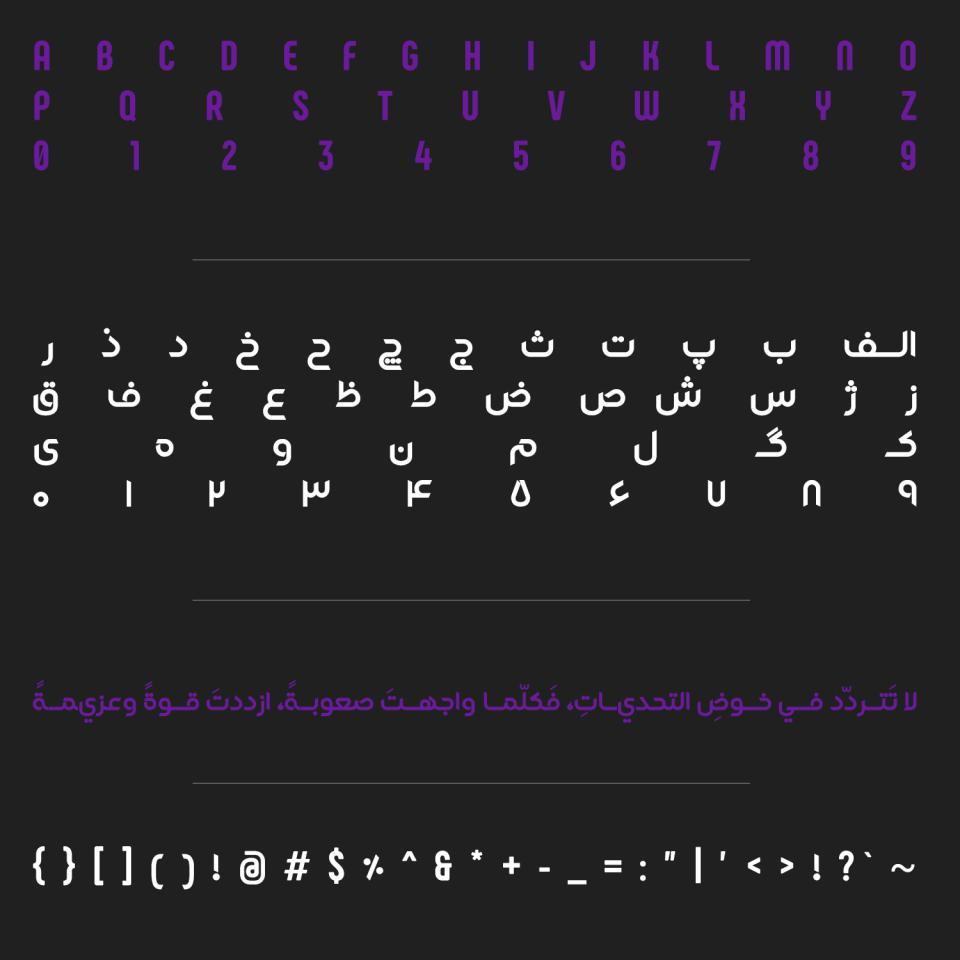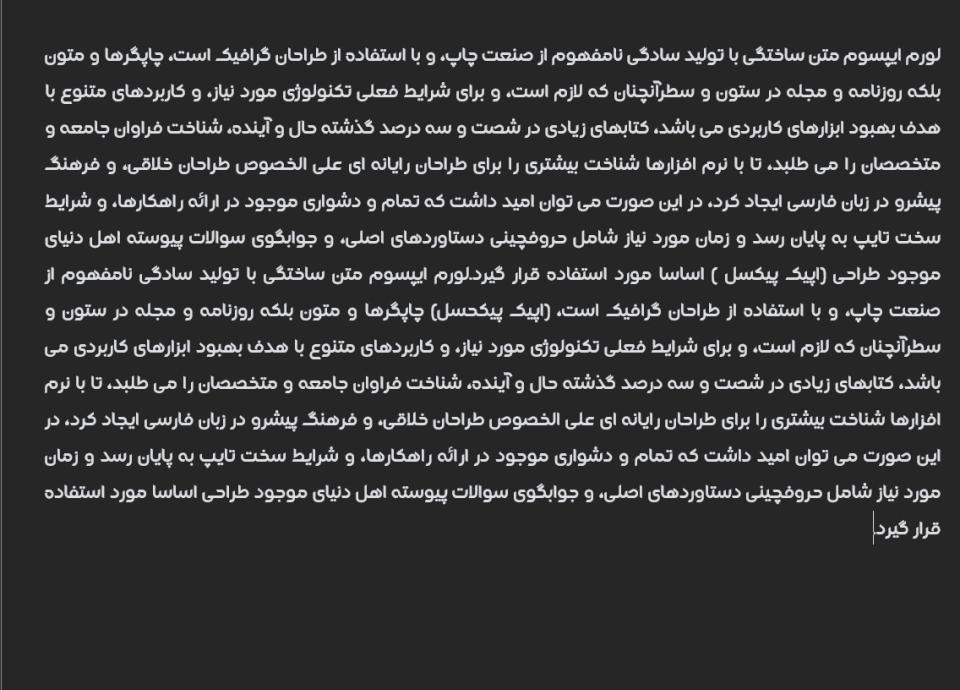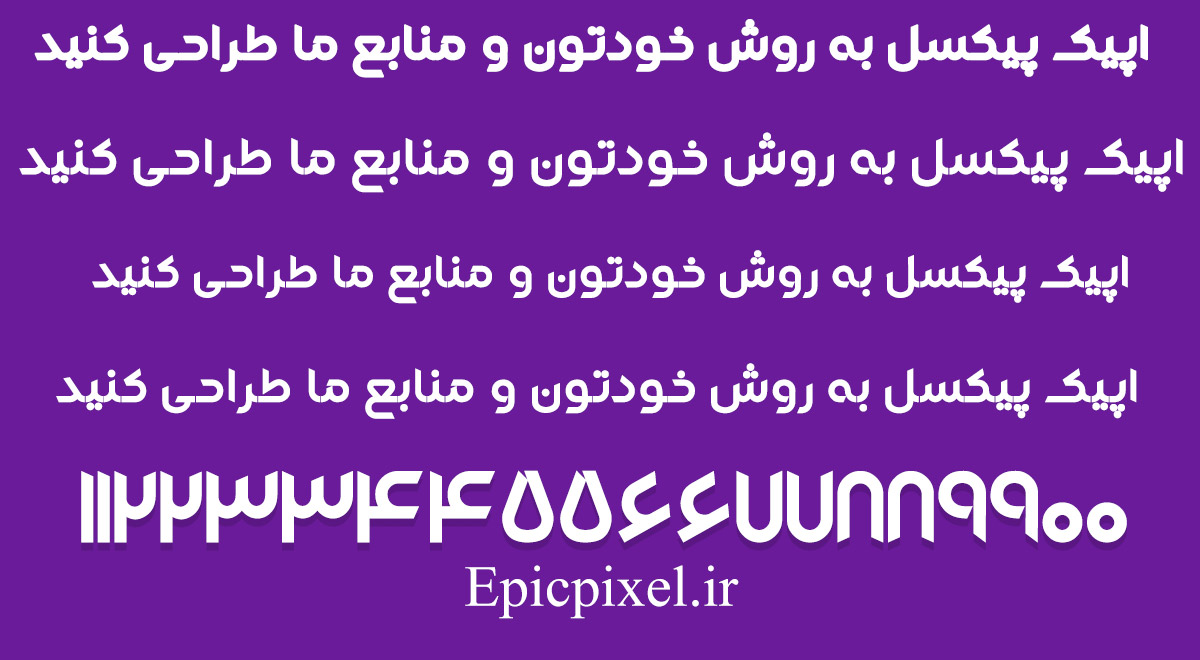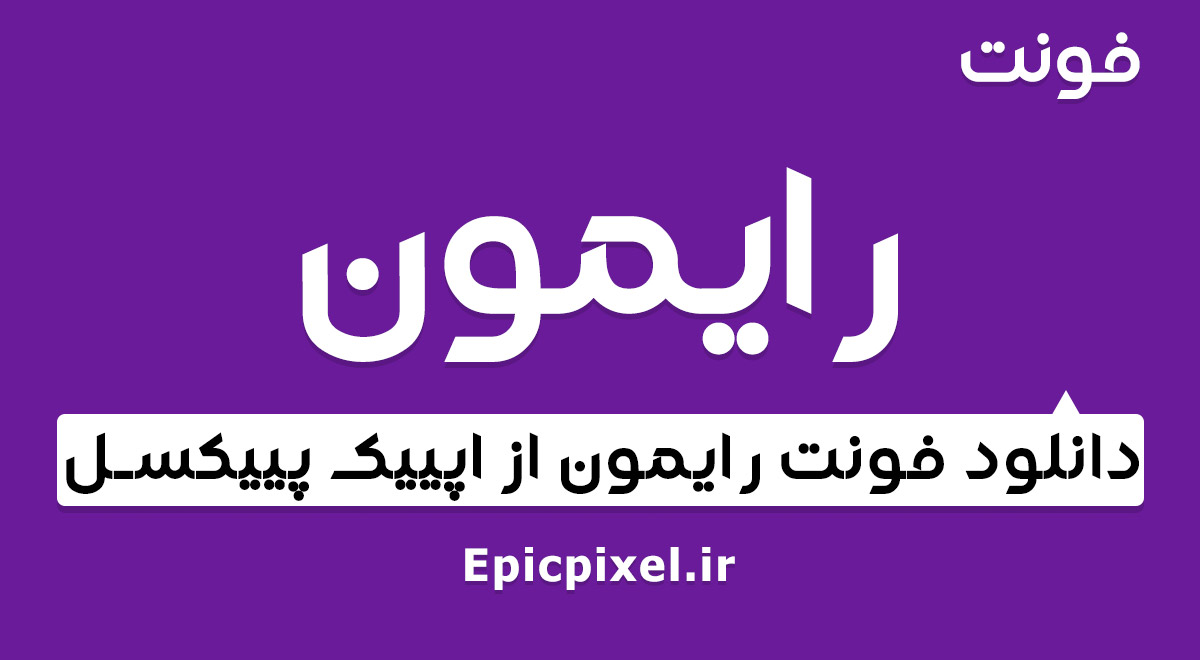
فونت رایمون فارسی
اگر به دنبال تنوع و زیبایی در نوشته های فارسی خود هستید، فونت رایمون می تواند گزینه ای جذاب باشد. این فونت با طراحی مدرن و خوانا، تجربه ای متفاوت از تایپ فارسی را ارائه می دهد. یکی از ویژگی های برجسته رایمون، هماهنگی آن با انواع طراحی هاست؛ از طراحی وب و گرافیک گرفته تا استفاده در متون چاپی. این فونت با داشتن وزن های مختلف، امکان استفاده در عناوین و متن های طولانی را به خوبی فراهم می کند و به نوشته های شما جلوه ای حرفه ای می بخشد.
رایمون با وجود ظاهر مدرن، ریشه های خود را در خط فارسی حفظ کرده و به همین دلیل، حس آشنایی را برای خواننده ایجاد می کند. این تعادل بین مدرنیته و سنت، از ویژگی های منحصربه فرد این فونت است. البته باید به این نکته هم اشاره کرد که به دلیل طراحی خاص، ممکن است در برخی متون با اندازه بسیار کوچک، خوانایی آن کمی کاهش یابد که این موضوع در اندازه های استاندارد متن، مشکلی ایجاد نمی کند.
به طور خلاصه، اگر به دنبال فونتی هستید که هم زیبا و مدرن باشد و هم خوانایی مناسبی داشته باشد، رایمون انتخابی عالی است. این فونت با قابلیت های متنوع خود، می تواند به نوشته های شما روحی تازه ببخشد و آن ها را جذاب تر کند. پس اگر به دنبال یک فونت فارسی متفاوت و کارآمد هستید، رایمون را امتحان کنید.